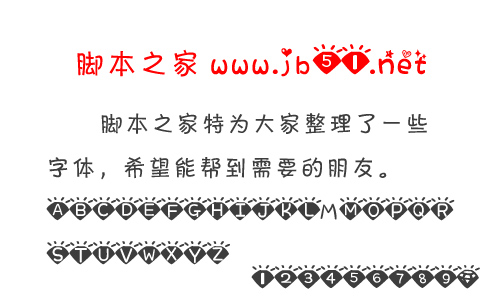
鉆石卡通簡體字體是非??蓯鄣目ㄍㄗ煮w,部分字母和數(shù)字會有鉆石的背景效果,能夠應(yīng)用于文本裝潢、信息展示、網(wǎng)頁設(shè)計、篆刻制模、數(shù)據(jù)制作、裝潢設(shè)計、計算藝術(shù)設(shè)計、視覺設(shè)計、字帖等一切合法應(yīng)用場景,歡迎有需要的朋友們前來下載使用。